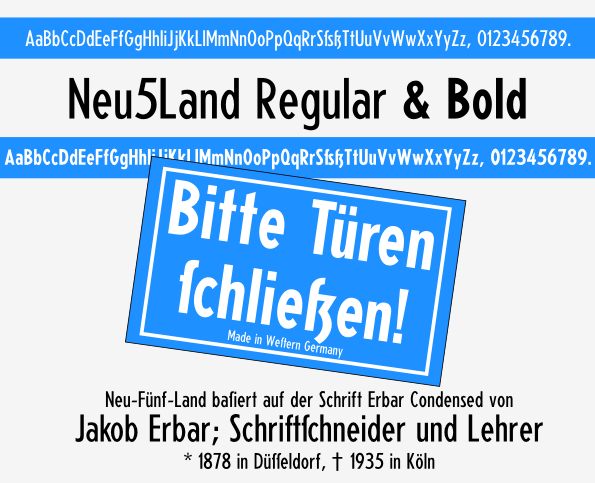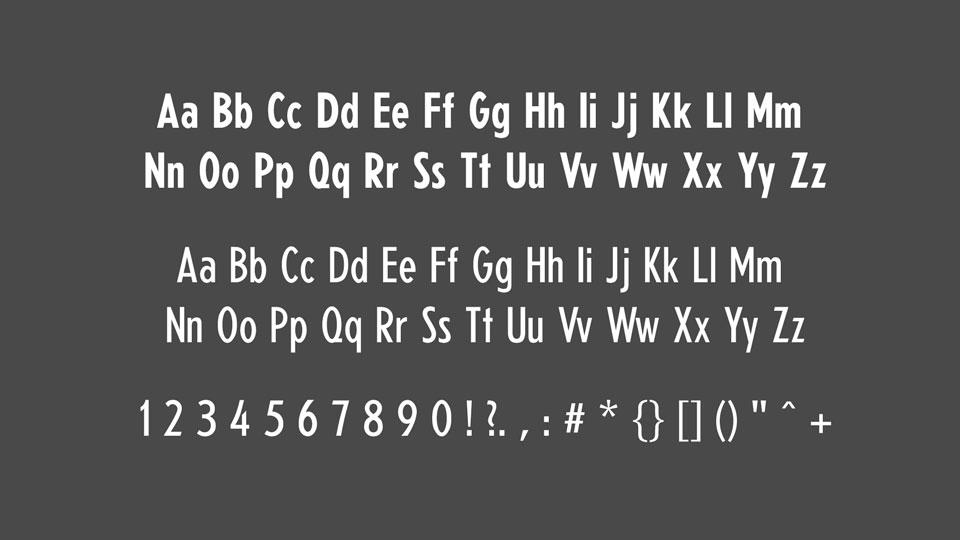
Schrift von DDR-Warn- und Hinweisschilder
wer  Schriften Ideologisch auf- oder abwertet müsste das auch bei Architektur tun. Ich bin da Ideologisch sowieso geheilt. keiner kann mir was gut oder schlecht reden ich bild mir mein eigenes Bild. Sozialismus ist ja auch schon 2x mis(t)braucht worden. Das war dann  eher Asozialismus. Egal Schriften haben zwar was mit Ideologie zu tun, aber im schlechtesten Sinne.
Aber mal im Ernst, wer sich mal das Datum angeschaut hat wann ich die Anfrage gestellt habe und Peter  für 50 Rubel das erste Ergebnis geliefert hat, grenzt schon an Magie. Ich wünschte ich wäre so schnell. Ich hab mich schon vor Jahren von Ideo-ten und -logie frei gemacht.
Ich stelle mir gerade vor, es gab die Zeit zwischen 33 und 89 nicht. Wenn man jetzt mal die Symbole jetzt als Logos verste3hen würde (IDEOLOGIEFREI!!!) wären das geniale Logos. Nimmt man dann noch die Schriften dazu ist das doch  die beste Kombination für ein Unternehmen.
Es gibt ja nicht viele Unternehmen die man nur anhand der Schrift oder das Logo  erkennt.  Ich betrachte Schriften immer als Kunstwerk, egal wann und für wen sie entworfen wurde.
Ok es gibt heute Schriften, die wie eine Schwemme daherkommen und mich gar nicht fesseln oder berühren. Ich hoffe ja dass das in der zweiten Hälfte des Jahrhundert wieder besser wird. Kein Wunder, dass wir eine Retrowelle erleben, weil man sich scheinbar nach ausdruckstarken Schriften sehnt.
Neu5land oder OstElbien. (östlich der Elbe) Ostelbia, wie man das auch immer genannt hat. Ich bin z.B. Berliner mit Integrationshintergrund. Früher hätte man da nur kurz Ossi gesagt
"Ossibar" find ich witzig, weil ich heute Ossi und Wessi als Qualitätsmerkmale sehe.
Soweit ich weiss wurde ja der Begriff Neu5land einerseits wegen der neuen 5 Länder so genannt, aber auch weil das arme Hunde waren (nein nicht wirklich) nur im Gedankengang vieler Wessis.
Heute kann ich über all diese Begriffe wirklich schmunzeln, Ossi als Schimpfwort gemeint kommt bei mir als Schulterklopfen an. so hat sich das mit den Jahren gewandelt.
Witzig finde ich das immer wieder wenn man gefragt wird woher man kommt. Als Berliner ist das ja heute nicht mehr so eindeutig. Ich lebe z.B. 3 Minuten vom Schloß Bellevue entfernt. ja was bin ich denn da, frage ich nicht selten. Da kommt doch oft die Antwort Wessi. Heute kann man daas nicht mehr am Wohnort festmachen. Gerade in Berlin. Wenn jetzt ein Türinger in Bayern landet , (huch da kommt noch das "H" rein, soll ja nicht als Türringer verstanden werden) , muss man nicht viel sagen man hörts halt. Ich persönlich find das immer schön wenn die Leute ihre Heimat auf der Zunge mitragen, solange man auch was versteht.
Deppen und ewig Gestrige gibts halt in allen Bundesländern ;-)
Oh achja Fritz heisst du. Nein man, ich heisse Friedrich. wusstest du das Iwan und Johannes das selbe bedeutet und Fritz und Friedrich auch?
Ab diesen Tag schrie der Deutsche den Russen nicht mehr an..... nach dem Krieg wurden sie sogar Freunde...und wenn sie nicht gestorben sind so leben sie noch heute.  Ach ja ich nenne den Deutschen mal Friedrich und den Russen Alexander.
Ich wurde mal von einem Russischen Soldaten damals, Mischka genannt, der mir auf der Fahrt von Berlin bis Wünsdorf (Hauptquatier der Ruissen in der DDR) das pfeifen aud den Fingern beibrachte.
Warum Mischka? nun ja ich bin Berliner und  war damals noch klein. Mischka bedeutet  kleines Bärchen ...   das passte dann auch gut zum  Kleinen Bärliner ;-)  eine andere Bedeutung ist медвежонок Medweschonok.
Das war für kleine deutsche Kinder zu schwer. Mischka ist übrigens auch der kleine Freund von Bummi und Maxel (Maxl). Hier kann man auch gut sehen wie unterschwellig ohne es zu bemerken die deutschen Farben den Kindern beigebracht wurden.
Im Mosaik ist das bei den Diggedags und den Abrafaxen auch so. Maxel , Mischka und Bummi (schwarz rot blond (gold) Mischka ist der schwarze Bär Maxel der braune und Bummi der Gelbe (blonde).
Da hab ich noch eine Handvoll Anmerkungen:
– Im Anmerkungstext fehlt ein "l" (gefettet) "… Demokratische Repubik (GDR/DDR)"
– Im Bild steht "… basiert auf der Schrift Erbar Condensed …" – hieß die nicht "Schmale …" wie im Anmerkungstext?
– Im Bild steht "Neu-Fünf-Land", benannt ist sie "Neu5Land"